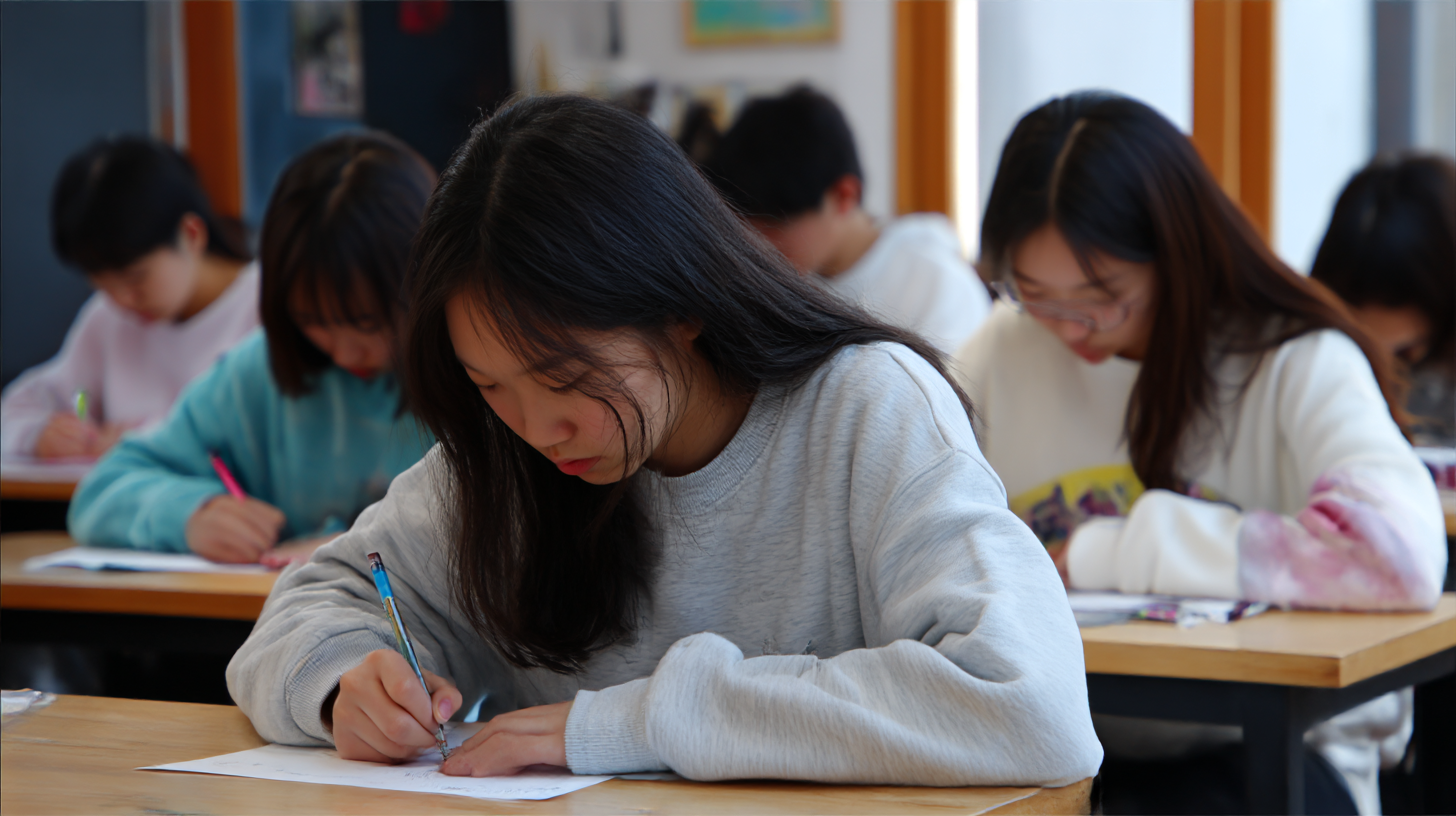
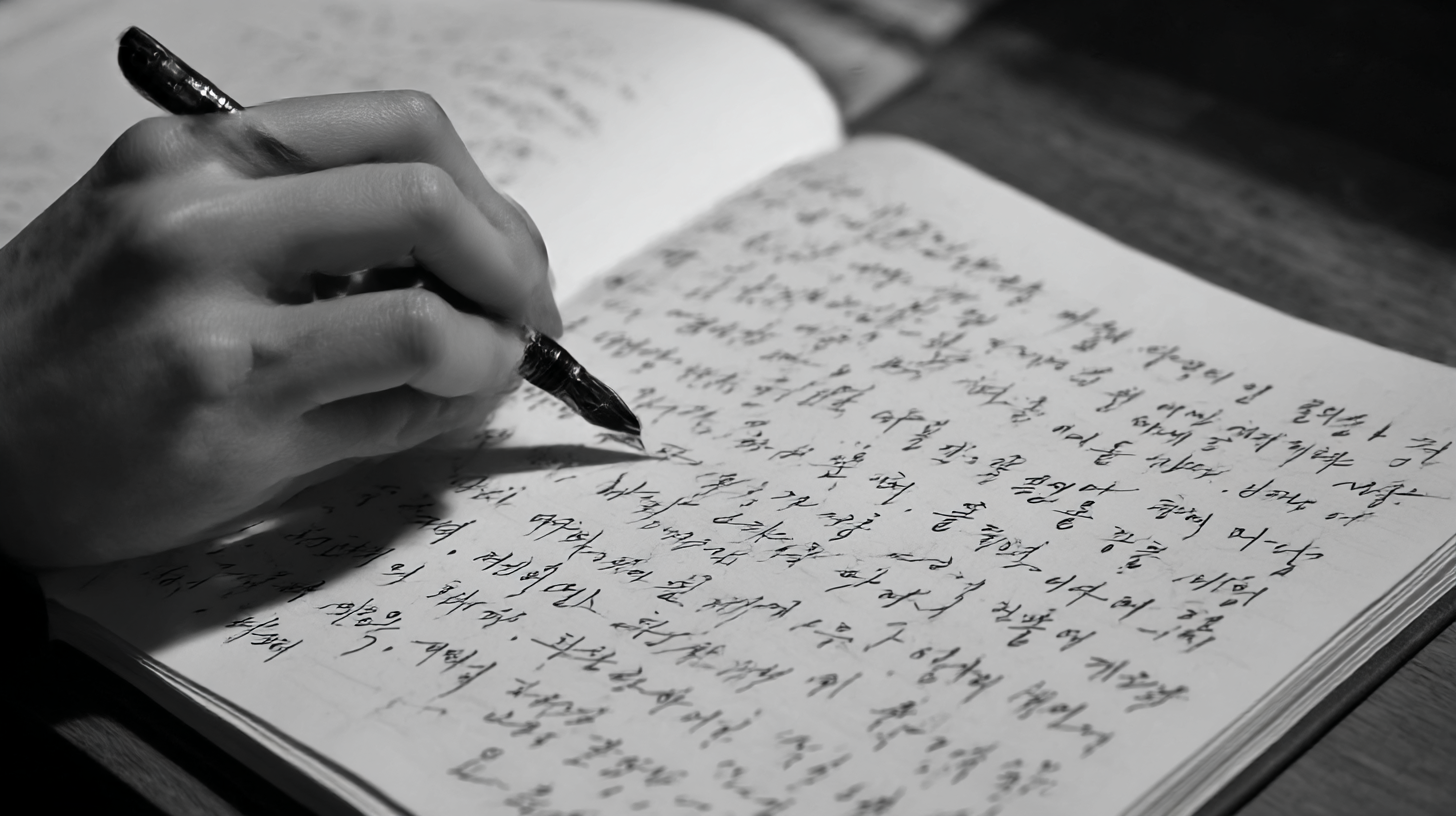
필기 속도가 느려지는 이유? 글씨 교정이 답일까? 필기 속도가 느려지는 이유는 다양해요. 손 근력이 부족하거나, 잘못된 필기 습관을 가지고 있거나, 지나치게 글씨를 예쁘게 쓰려고 신경 쓰는 경우가 많죠. 하지만 이런 문제들은 조금만 노력하면 충분히 개선할 수 있어요.
특히 필기 속도를 높이려면 바른 자세, 효율적인 그립법, 그리고 적절한 연습이 중요해요. 또한, 글씨 교정을 하면 속도뿐만 아니라 가독성도 함께 좋아지기 때문에 큰 도움이 된답니다. 지금부터 필기 속도가 느려지는 원인과 해결 방법을 차근차근 알아볼게요! ✍
📌 필기 속도가 느려지는 원인
필기 속도가 느려지는 이유는 사람마다 다를 수 있지만, 몇 가지 대표적인 원인이 있어요. 이 원인들을 파악하면 필기 속도를 높이는 데 큰 도움이 될 거예요.
1. 글씨를 너무 정성스럽게 쓰려는 습관
예쁜 글씨를 쓰려다 보면 자연스럽게 필기 속도가 느려질 수밖에 없어요. 특히 학생들이나 업무 중 메모를 많이 하는 직장인들은 빠른 속도로 글씨를 써야 할 때가 많죠. 하지만 글씨를 정갈하게 쓰려고 하면 속도가 느려질 수밖에 없어요.2. 손 근력 부족
오랫동안 필기를 하지 않으면 손 근력이 약해져서 필기 속도가 줄어들어요. 특히 손목이나 손가락 힘이 부족한 경우, 필기를 할 때 쉽게 피로감을 느끼고 속도가 떨어질 수 있어요.3. 잘못된 필기 자세와 그립법
손가락이나 손목의 움직임이 비효율적이라면 필기 속도가 느려질 수밖에 없어요. 연필을 너무 세게 잡거나, 손목을 지나치게 구부리면 글씨를 쓰는 데 불필요한 힘이 들어가 속도가 느려질 수 있어요.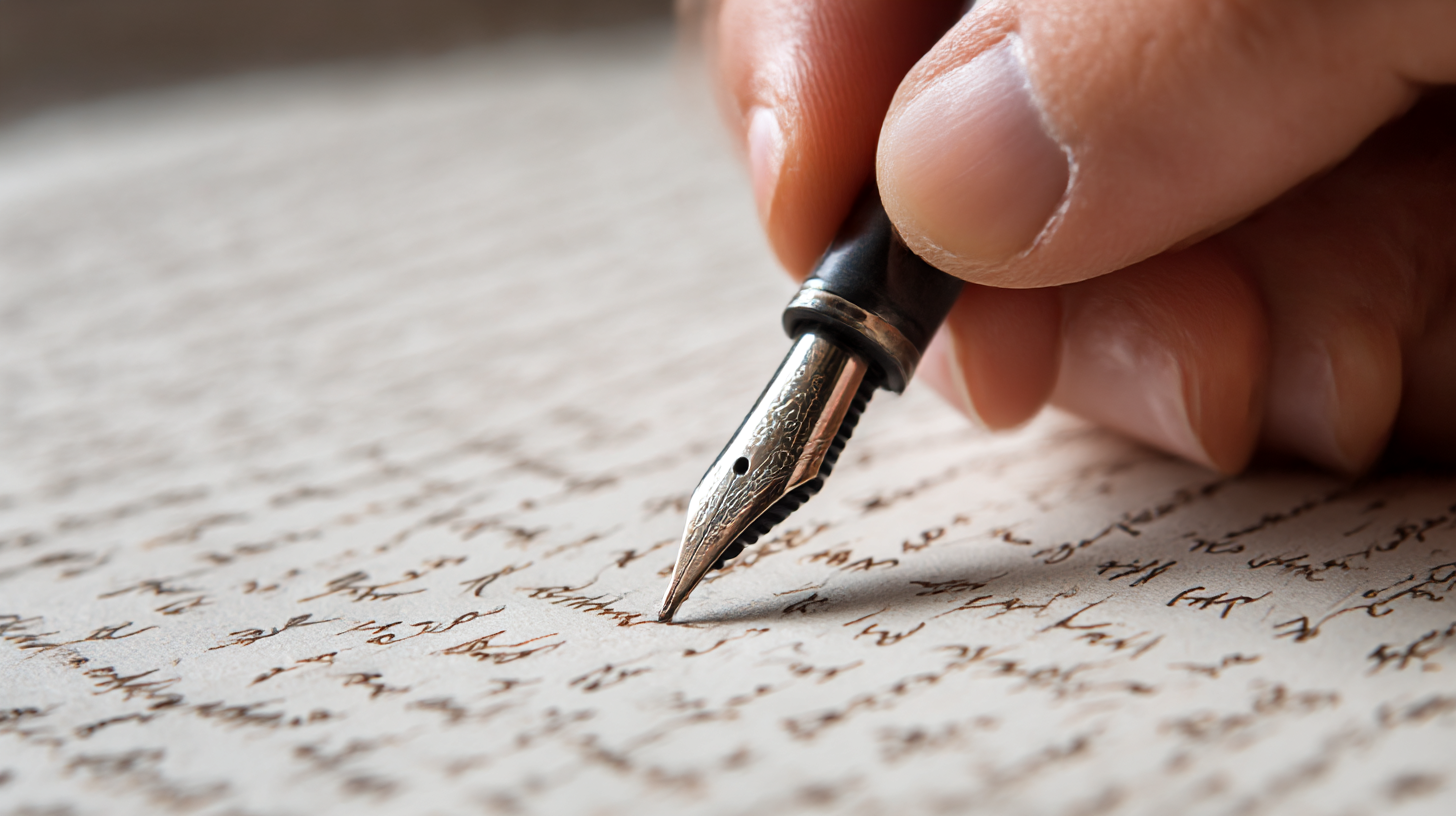
필기 속도가 느려지는 원인 📊 필기 속도 저하 원인 비교
원인 영향 해결 방법 글씨를 너무 예쁘게 쓰려는 습관 필기 속도 저하, 피로 증가 적절한 속도로 쓰는 연습 손 근력 부족 빠르게 필기하면 손이 쉽게 피로해짐 손 근력 강화 운동 잘못된 필기 자세 불편한 손 움직임, 속도 저하 올바른 자세와 그립법 교정 필기 속도를 높이려면 먼저 본인의 문제점을 파악하는 게 중요해요. 내가 생각했을 때, 가장 중요한 것은 자세 교정과 꾸준한 연습이에요! ✨
🖊 바른 필기 자세와 그립법
필기 속도를 높이려면 바른 자세와 적절한 펜 잡는 법이 필수예요. 잘못된 자세로 필기하면 손이 쉽게 피로해지고 속도도 느려질 수밖에 없어요. 그러니 올바른 필기 자세를 익히는 게 중요해요!
1. 바른 필기 자세
필기할 때는 허리를 곧게 펴고 책상과 몸 사이의 거리를 적절히 유지해야 해요. 고개를 너무 숙이면 목에 부담이 가고, 등을 구부리면 오래 필기하기 어려워요.2. 적절한 펜 잡는 법
펜을 너무 꽉 쥐면 손이 금방 피로해지고 속도가 느려져요. 손가락 세 개(엄지, 검지, 중지)로 펜을 가볍게 잡고, 손목과 팔 전체를 이용해 필기하는 게 좋아요.📝 올바른 필기 자세 체크리스트
항목 바른 자세 잘못된 자세 허리 자세 등을 곧게 펴고 앉기 구부정하게 앉기 펜 잡는 법 가볍게 잡기 너무 꽉 쥐기 손목 사용 팔과 함께 움직이기 손가락만 사용 올바른 필기 자세를 유지하면 필기 속도가 훨씬 빨라질 뿐만 아니라 손의 피로도도 줄어들어요. 😊
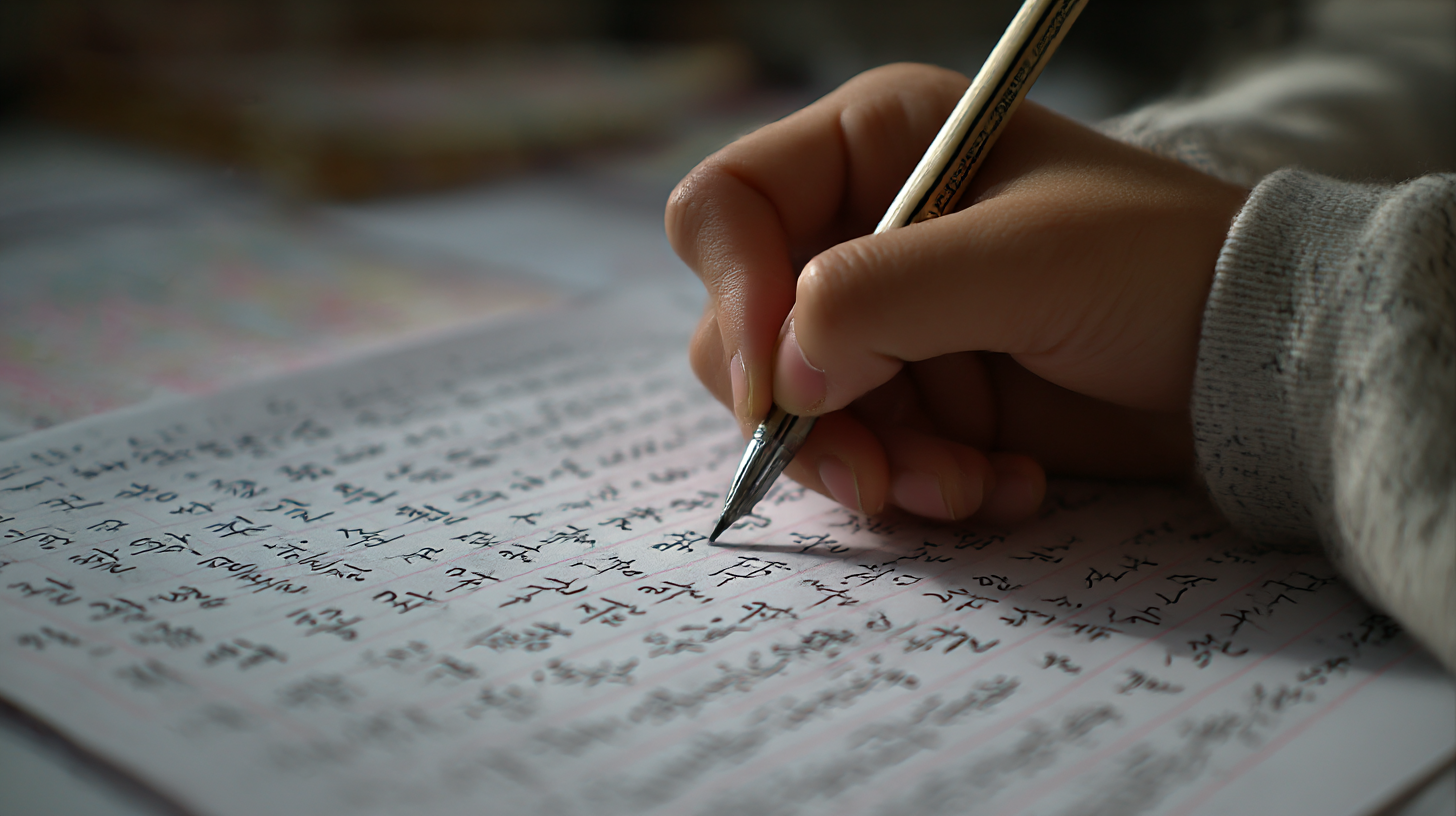
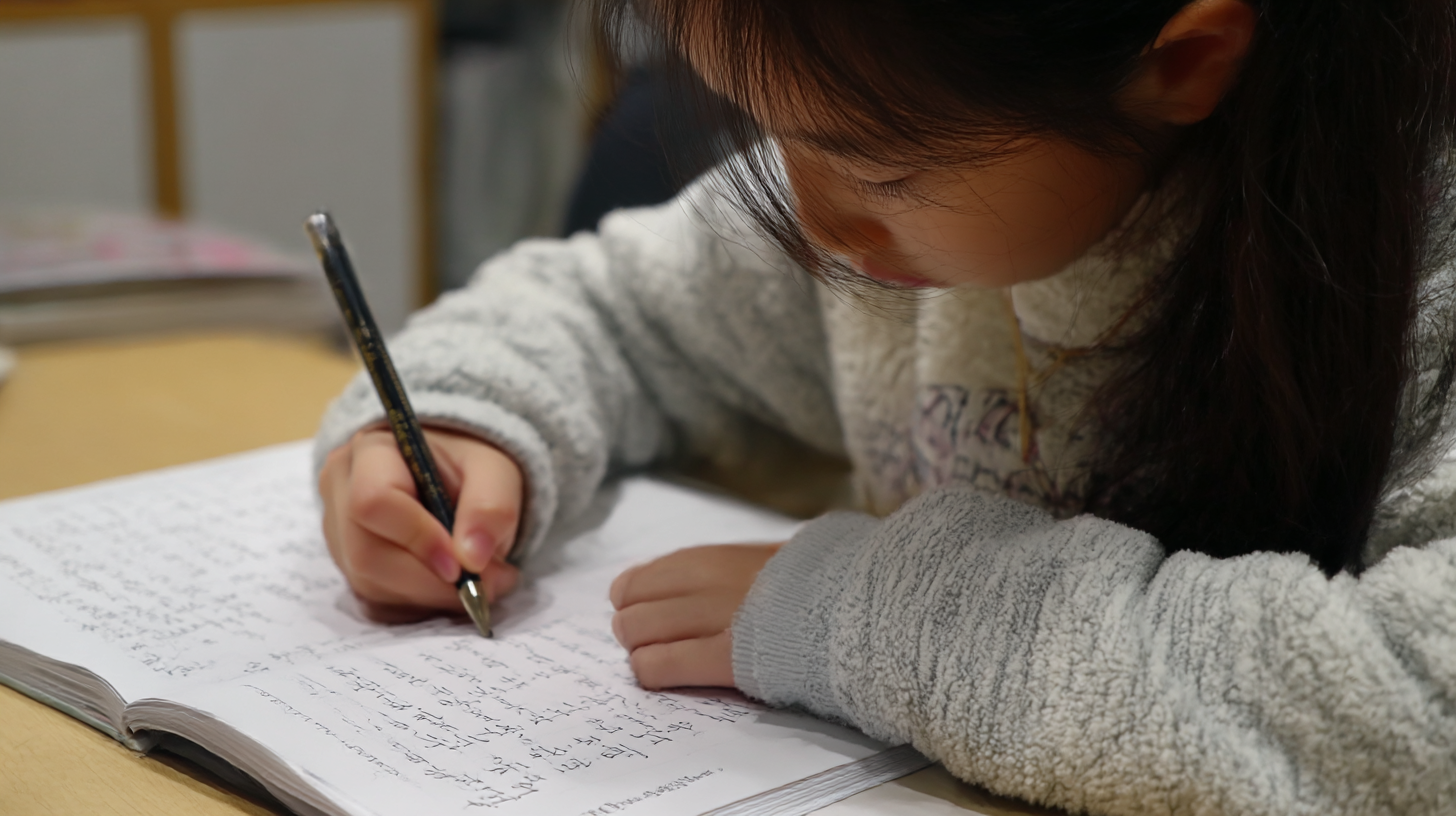
바른 필기 자세와 그립법 🏃♂ 필기 속도 향상을 위한 연습법
필기 속도를 높이기 위해서는 꾸준한 연습이 필수예요. 단순히 많이 쓰는 것보다, 효과적인 방법으로 연습해야 해요. 몇 가지 연습법을 소개할게요!
1. 타이머를 활용한 속도 필기
정해진 시간 안에 최대한 많이 쓰는 연습을 해보세요. 예를 들어, 1분 동안 특정 문장을 반복해서 써보고 개수를 체크하는 방식이에요.2. 간결한 필기 연습
필기를 빠르게 하려면 글자를 너무 작거나 복잡하게 쓰지 않는 것이 중요해요. 최대한 단순하고 깔끔한 필체로 연습해 보세요.🖊 필기 속도 향상 훈련법
연습 방법 설명 효과 타이머 필기 정해진 시간 내에 최대한 많은 글자 쓰기 속도 향상, 집중력 증가 짧은 문장 반복 반복적인 문장 필기 연습 손의 유연성 향상 간결한 필체 연습 복잡한 글씨 대신 간결한 필기법 사용 가독성 증가, 속도 향상 이런 연습을 꾸준히 하면 필기 속도가 자연스럽게 빨라질 거예요.✍
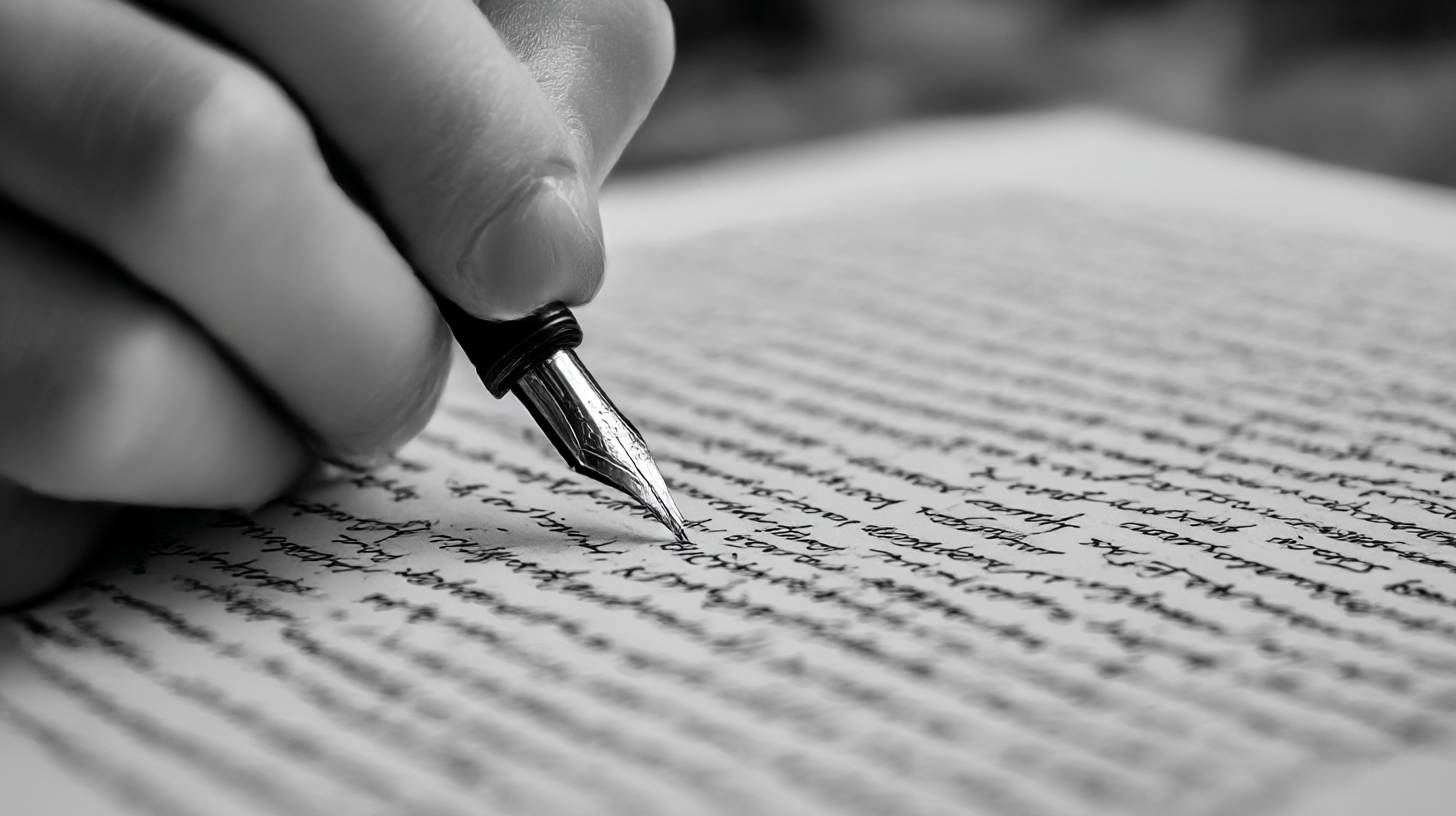
필기 속도 향상을 위한 연습법 ✍ 글씨체 교정이 필기 속도에 미치는 영향
많은 사람들이 "글씨를 예쁘게 쓰면 필기 속도가 느려지지 않을까?"라고 생각하는데, 꼭 그렇지는 않아요. 오히려 글씨체를 효율적으로 교정하면 필기 속도를 높일 수 있어요! 😊
1. 불필요한 획을 줄이기
너무 꾸미는 글씨체보다는 간결한 필체가 필기 속도를 높여줘요. 획이 많은 글씨체를 쓰면 자연스럽게 속도가 느려질 수밖에 없어요.2. 글씨 크기 조절하기
너무 크거나 작은 글씨는 필기 속도를 늦추는 원인이 될 수 있어요. 적당한 크기의 글씨를 유지하는 것이 가장 좋아요.📝 글씨체 교정 전후 비교
항목 교정 전 교정 후 글씨 크기 불규칙, 크기가 일정하지 않음 적절한 크기로 일정하게 유지 획의 복잡성 불필요한 장식이 많음 간결하고 효율적인 필기 가독성 읽기 어려움 빠르게 써도 쉽게 읽힘 이처럼 글씨체를 조금만 다듬어도 필기 속도가 빨라질 수 있어요! 🎯
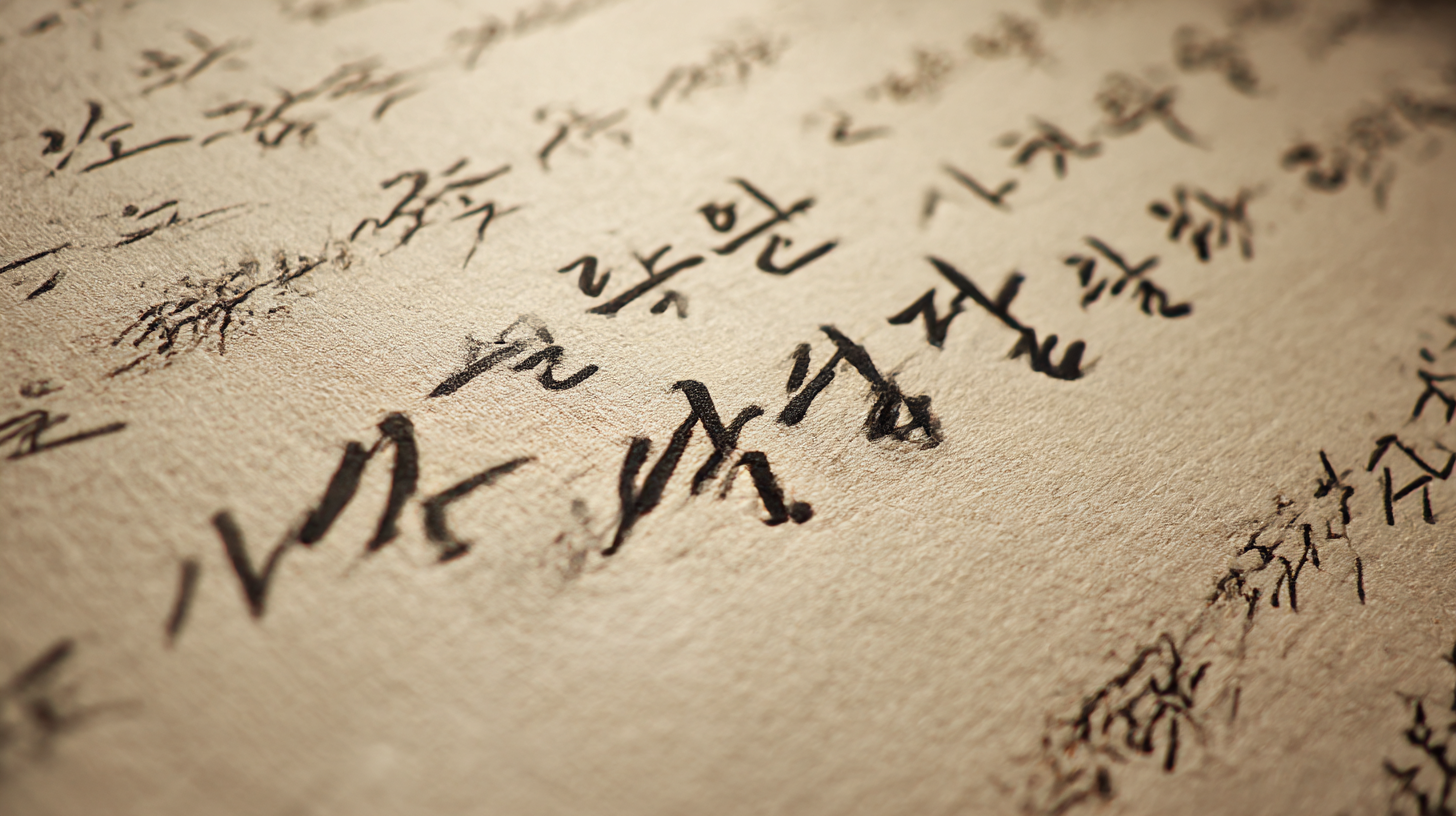
글씨체 교정이 필기 속도에 미치는 영향 📱 디지털 필기 vs 손글씨 필기, 뭐가 더 좋을까?
요즘에는 태블릿이나 노트북으로 필기하는 사람들이 많아졌어요. 하지만 손글씨 필기를 선호하는 사람도 여전히 많죠. 과연 어느 방식이 더 효율적일까요? 🤔
1. 디지털 필기의 장점
디지털 필기는 빠르게 입력할 수 있고, 수정도 간편해요. 특히 태블릿을 이용하면 필기 내용이 깔끔하게 정리되기 때문에 노트 정리할 때 유용하죠.2. 손글씨 필기의 장점
손으로 직접 쓰는 필기는 기억력과 집중력을 높이는 데 도움이 돼요. 연구에 따르면, 손으로 필기할 때 뇌의 활동이 더 활발해져서 내용을 더 잘 기억할 수 있다고 해요.💡 디지털 필기 vs 손글씨 필기 비교
비교 항목 디지털 필기 손글씨 필기 속도 빠름 비교적 느림 수정 편리성 간편하게 수정 가능 수정이 어려움 기억력 향상 비교적 낮음 높음 가독성 항상 일정함 개인차 있음 각각의 장단점이 있기 때문에, 상황에 따라 적절한 방법을 선택하는 것이 좋아요. 😊
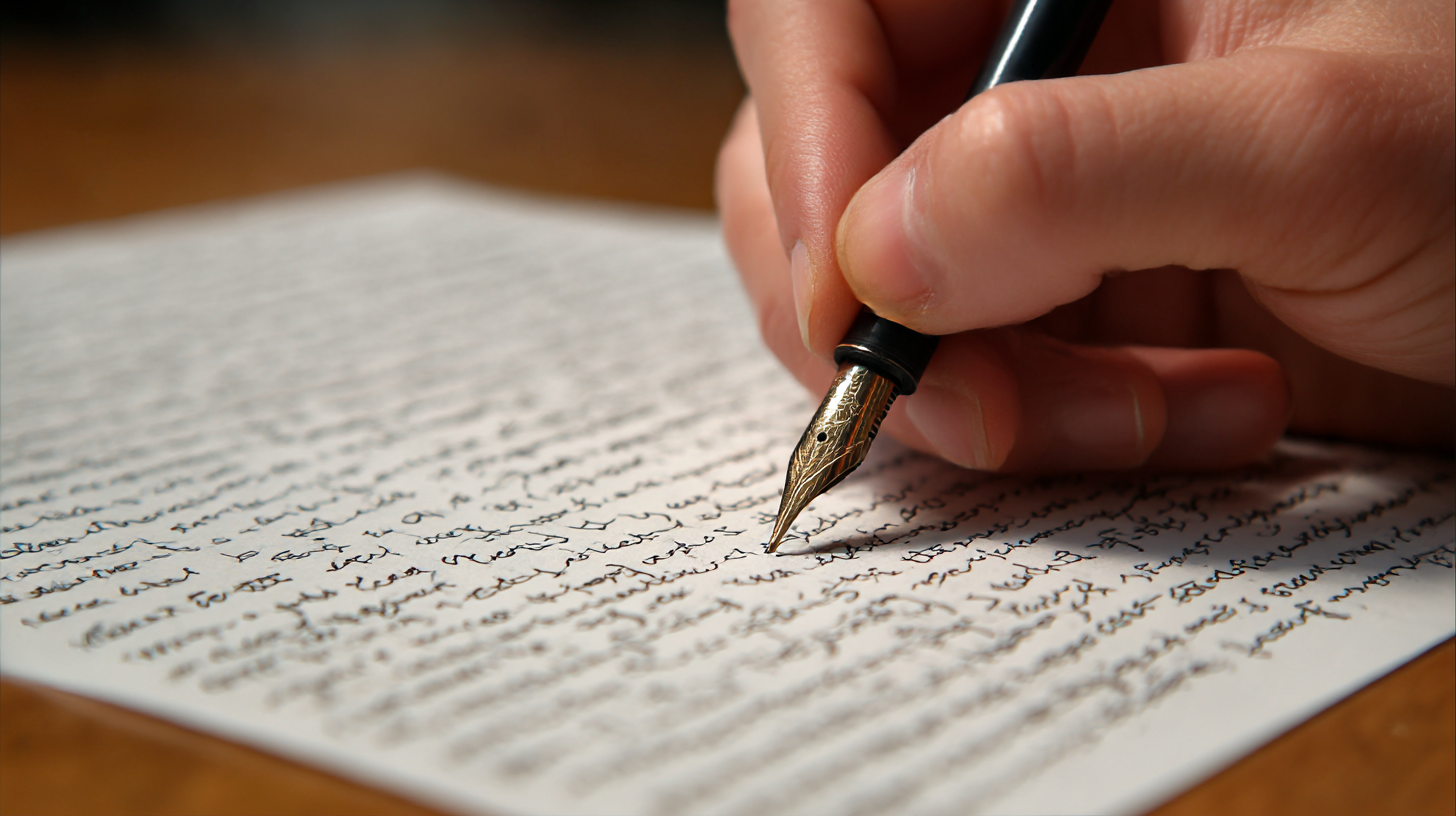
디지털 필기 vs 손글씨 필기, 뭐가 더 좋을까? 🖊 필기 속도를 높여주는 추천 도구
필기 속도를 높이려면 연습도 중요하지만, 좋은 필기 도구를 사용하는 것도 큰 도움이 돼요. 손에 맞는 필기구를 사용하면 피로감을 줄이고, 필기 효율을 높일 수 있어요! ✍
1. 필기감이 좋은 펜 선택하기
펜마다 필기감이 다르기 때문에 손에 맞는 펜을 찾는 것이 중요해요. 가볍고 부드럽게 써지는 펜이 필기 속도를 높이는 데 유리해요.2. 편한 노트 선택하기
종이 질이 너무 거칠거나 미끄러우면 필기 속도가 떨어질 수 있어요. 적당한 마찰력을 가진 노트가 손에 부담을 줄여줘요.📌 필기 속도 향상 추천 도구
도구 추천 브랜드 특징 볼펜 제트스트림, 사라사 부드러운 필기감, 빠른 속도 젤펜 모나미 플러스펜, 유니볼 시그노 선명한 글씨, 부드러운 터치 노트 몰스킨, 롤러본드 적당한 마찰감, 깔끔한 필기 태블릿 아이패드, 갤럭시탭 디지털 필기, 빠른 정리 좋은 필기 도구를 활용하면 필기 속도가 빨라질 뿐만 아니라 글씨도 훨씬 깔끔해져요. 😊
필기 속도를 높여주는 추천 도구 ❓ FAQ
Q1. 필기 속도를 높이는 가장 효과적인 방법은 무엇인가요?
A1. 가장 효과적인 방법은 타이머를 설정하고 빠르게 쓰는 연습을 반복하는 거예요. 또한, 바른 필기 자세와 적절한 펜을 사용하는 것도 중요해요.
Q2. 글씨를 예쁘게 쓰면 필기 속도가 느려지나요?
A2. 꼭 그렇지는 않아요. 불필요한 획을 줄이고 간결한 필체로 교정하면 속도와 가독성을 동시에 향상시킬 수 있어요.
Q3. 필기할 때 손이 쉽게 피로해지는 이유는?
A3. 펜을 너무 꽉 쥐거나 손목을 많이 사용하면 피로가 빨리 와요. 손가락과 손목의 힘을 적절히 분배하고 가볍게 필기하는 연습이 필요해요.
Q4. 디지털 필기와 손글씨 필기 중 어느 것이 더 좋을까요?
A4. 상황에 따라 달라요. 디지털 필기는 정리하기 쉽고 빠르지만, 손글씨 필기는 기억력을 향상시키는 데 더 효과적이에요.
Q5. 필기 속도를 높이는 데 가장 좋은 펜은?
A5. 부드러운 필기감을 가진 볼펜이나 젤펜이 좋아요. 제트스트림, 사라사 같은 제품이 필기 속도를 높이는 데 도움이 돼요.
Q6. 글씨 크기는 필기 속도에 영향을 미치나요?
A6. 네, 너무 크거나 작은 글씨는 속도를 늦출 수 있어요. 적당한 크기의 글씨를 유지하는 것이 중요해요.
Q7. 필기 연습을 할 때 어떤 문장을 연습하는 게 좋을까요?
A7. 짧고 반복적인 문장을 연습하는 것이 좋아요. 예를 들어, "빠른 갈매기처럼 써보자!" 같은 문장을 여러 번 써보세요.
Q8. 필기 속도를 높이는 데 걸리는 시간은 얼마나 되나요?
A8. 개인마다 다르지만, 하루 10~15분씩 꾸준히 연습하면 2~3주 내에 효과를 볼 수 있어요!